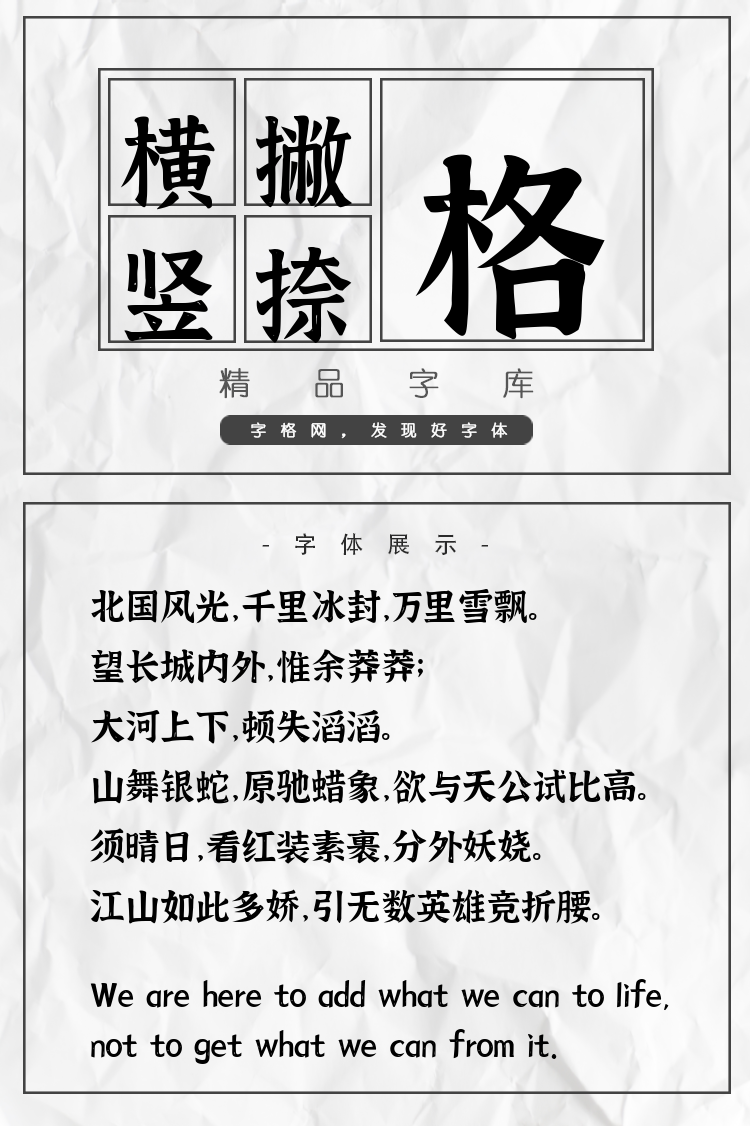
江西拙楷2
字体说明:江西拙楷2字体是一款可商用的毛笔书法,英文手写,手写体字体,该字体包含6763个中文、字母、符号和数字,具有充满力量、大气、豪放、稳重、手写风、古典 的风格,可以满足您设计上的各种需求,该字体主要用于电商、广告、视频影视、海报企宣、书籍 等场景, 您不但可以在字格网下载江西拙楷2,同时还有众多毛笔书法字体、创意字体等可供选择!